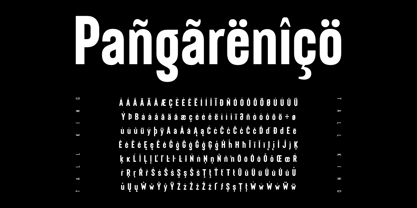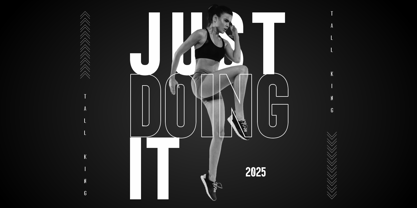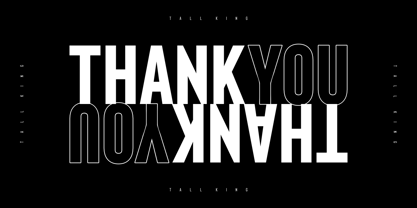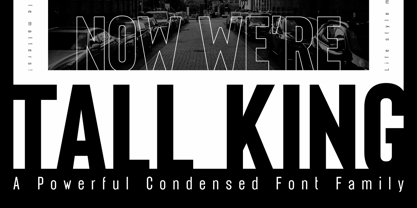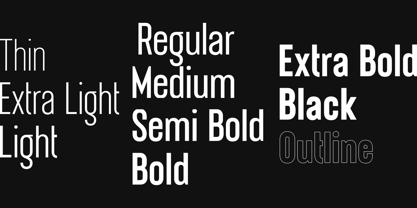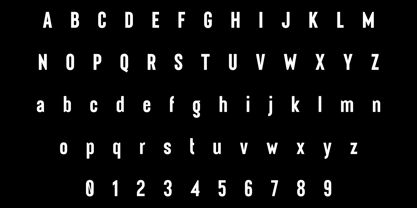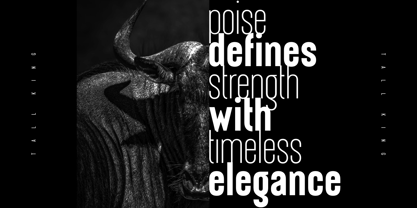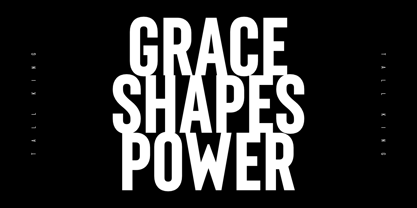
Tall King
Die Schriftfamilie Tall King wurde von Alfin Weniardi entworfen und von Lone Army veröffentlicht. Tall King enthält 10 Stile und Familienpaketoptionen.
Discover our latest condensed font: a perfect blend of strength and elegance. Designed for impactful headlines and sophisticated branding, it delivers style and clarity in every character.